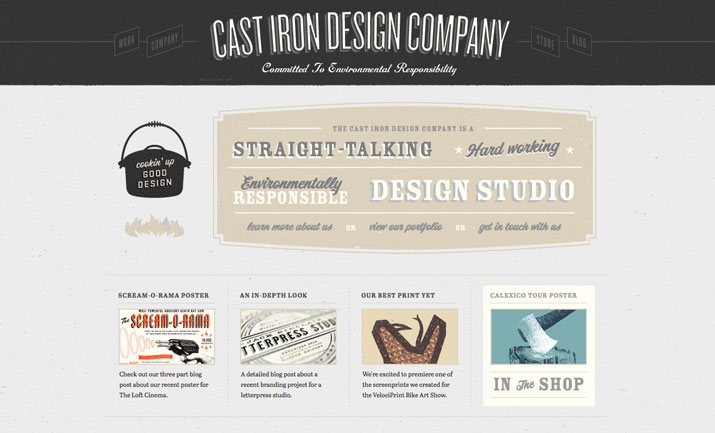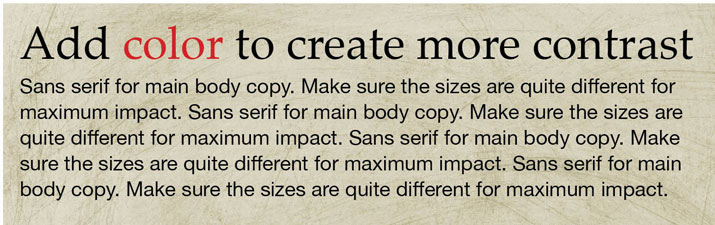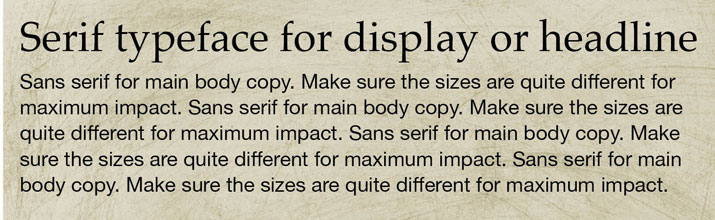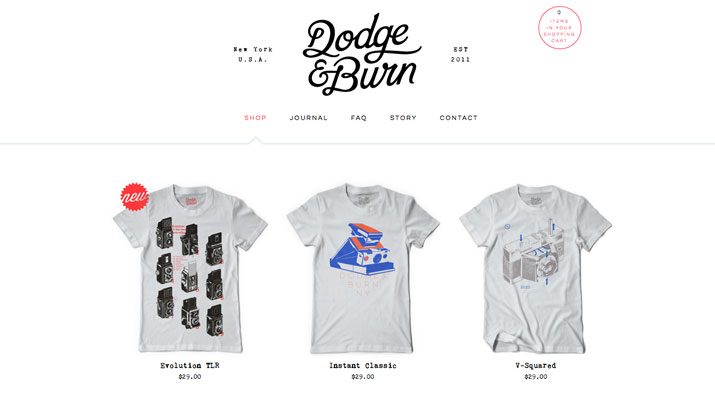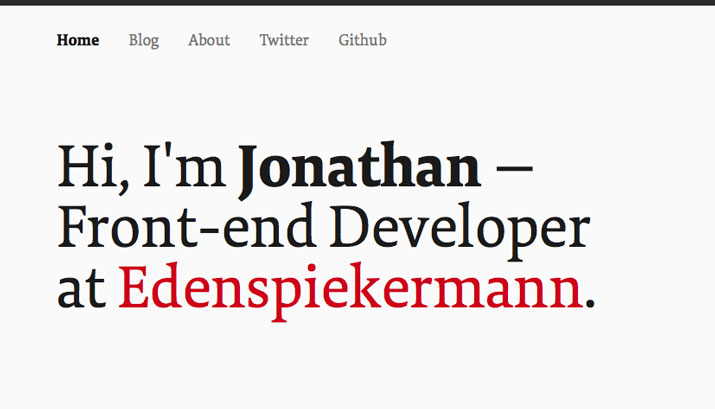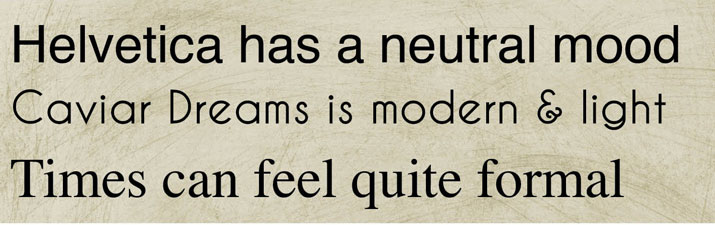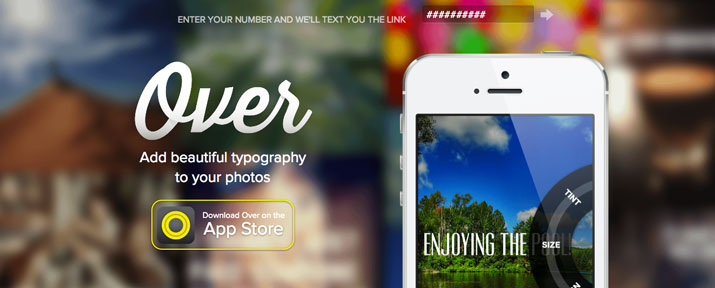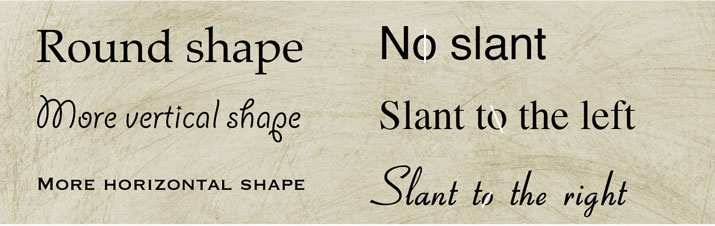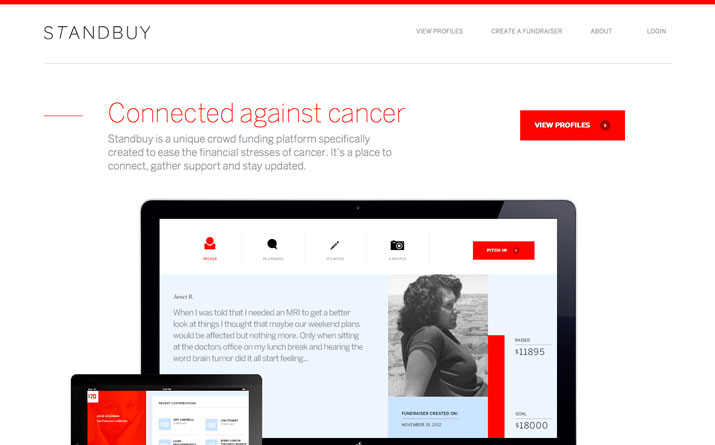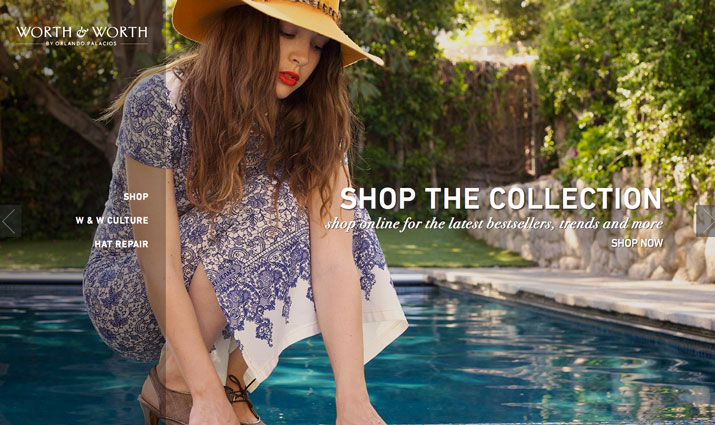
Комбинирование шрифтов: подсказки и техники
Комбинирование шрифтов может быть очень важным и увлекательным процессом во время создания дизайна. Идеальное сочетание начертаний может сделать ваш проект действительно потрясающим и при этом читабельным. Но с чего начать? На что обращать внимание при комбинировании шрифтов? И хотя сложно дать строго однозначные ответы на эти вопросы, есть несколько вещей, которые стоит иметь в виду. Думайте о контрасте, о величине очка шрифта, форме и общем настроении. В этой публикации мы поговорим о каждом из этих моментов подробнее.
С чего начать?
Несмотря на то, что они противоречат друг другу, основными принципами комбинирования цветов являются различие и соответствие. Подбирайте шрифты так, чтобы их отличия друг от друга были очевидны, но сочетайте их так, чтобы вместе они производили нужное впечатление.
Еще одна вещь, о которой нужно подумать при комбинировании шрифтов — их количество. Не усложняйте — обычно чем меньше шрифтов использовано в проекте, тем лучше. Начните всего с двух семейств шрифтов. Этого достаточно для большинства проектов, особенно, если вы новичок в этом деле.
Чтобы обеспечить достаточные различия между шрифтами, создавайте контраст, сочетая шрифты из разных категорий, разных размеров и толщины. А чтобы шрифты соответствовали другу другу, выбирайте начертания с одинаковой величиной очка, формой, наклоном и настроением.
Создайте контраст между шрифтами
Создать контраст между шрифтами можно несколькими способами: выбирая гарнитуры из разных категорий, разной толщины и размера, или при помощи цвета.
Один из самых простых способов создания такого контраста — комбинирование шрифтов с засечками и без. В веб-дизайне шрифты без засечек обычно используются для общего текста, а шрифты с засечками — для заголовков и надписей. В полиграфии популярнее противоположная комбинация. Этот принцип один из самых простых для сочетания шрифтов, и чаще всего такая комбинация наиболее читабельна.
Шрифты без засечек также отлично сочетаются с самыми разными типами гарнитур. Некоторые проекты шикарно смотрятся при сочетании рукописного или декоративного шрифта со шрифтом без засечек. Ключ ко всему — читабельность. Если вы выбираете сложно читаемый шрифт, сделайте его большого размера и используйте всего для нескольких слов, как на арт-постерах.
Контраст также можно создать при помощи размера. Используйте разные размеры шрифта в разных частях проекта. Сначала определитесь с кеглем общего шрифта, затем заметно увеличьте размер для надписей. Помните что самым большим шрифтом должно быть  отмечено самое важное. Избегайте шрифтов, которые выглядят одинаково. Этот недостаток контраста может нарушить визуальной баланс всего проекта.
Жирные, тяжелые шрифты с толстыми штрихами всегда выглядят больше. Используйте их в сочетании с тонкими, нормальными шрифтами  чтобы создать контраст.
И наконец подумайте о том, как можно создать контраст при помощи цвета. Чаще всего используются шрифты черного и белого цветов, но при помощи цветных оттенков можно акцентировать внимание там, где вам нужно. Подумайте о том, чтобы акцентировать шрифт цветом, используя тот же оттенок во всем проекте.
Учитывайте величину очка шрифта
Очко шрифта характеризует величину строчного знака относительно кегля шрифта и величины прописного знака. Иными словами это размер расстояния между большой и маленькой буквами шрифта. При комбинировании гарнитур следите за тем, чтобы этот параметр был одинаковым.
Вы можете даже немного хитрить и подгонять расстояния вручную, например, изменяя размер прописного шрифта в немногословных надписях. Это особенно важно в работах где разные шрифты используются в одинаковых блоках или когда разные шрифты располагаются в одном ряду.
Формы и наклон
Шрифты с похожими характеристиками довольно просто сочетать. Обращайте внимание на общую форму шрифтов, толщину, стиль засечек и наклон букв.
Смотрите на форму овалов (изогнутые штрихи в букве), внутрибуквенный просвет, и форму букв в целом. Насколько они различны? Обычные, нормальные шрифты как правило отлично сочетаются со всем, а вот очень жирные, короткие, вытянутые, тонкие или сжатые буквы могут визуально подавлять и смотреться не к месту.
Овалы и внутрибуквенный просвет — отличные меры измерения. В шрифтах, которые хорошо сочетаются, эти элементы схожей формы и размера, даже если речь идет о разных типах гарнитур. Обращайте внимание на то открыт или закрыт внутрибуквенный просвет, схожи ли формы.
Толщина штрихов попадает под то же правило. Сочетайте шрифты со схожей толщиной штрихов. То же можно сказать и стилях засечек. Смотрите на их толщину, объем, детальность.
Также обращайте внимание на угол наклона буква. Избегайте использование шрифтов с противоположным углом наклона. Для того, чтобы определить угол наклона смотрите на прописную букву “o.”
Итоги
Когда дело доходит до реальной работы, лучший путеводитель по комбинированию шрифтов — ваш вкус. Если что-то смотрится не очень, пробуйте что-то другое. Если вы нашли идеальное сочетание, которое может не отвечать некоторым правилам, забудьте о правилах.